最是一年春色好,草青水绿景色好。时光荏苒,匆匆间就来到了春分时节。万物复苏,春回大地,这样的美景当然要有好的字体来相配了。
今天给大家带来的是一组充满春日气息的海报,一起来欣赏
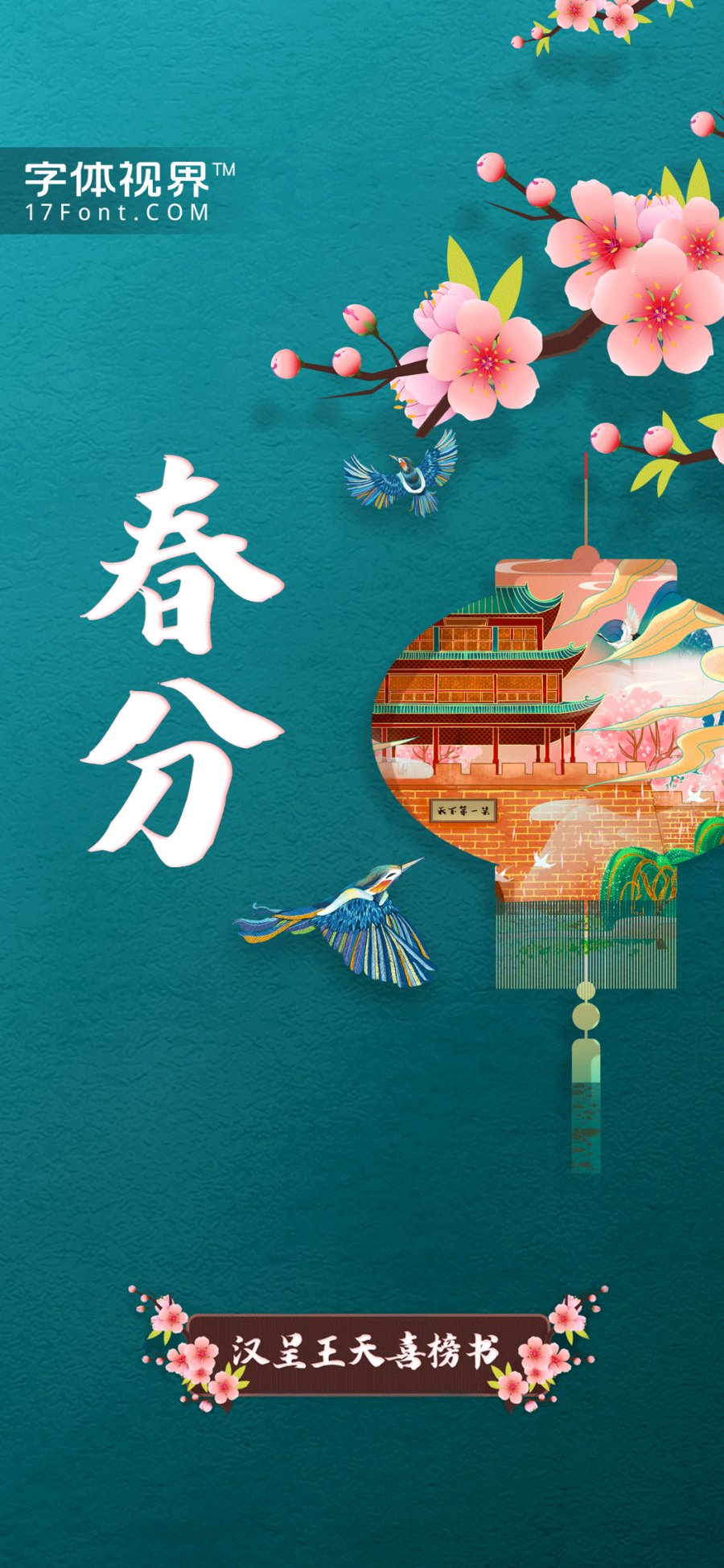
汉呈王天喜榜书字体是典型的行楷字体风格,看上去非常的端正秀美,充满了古典气息。字体可以应用于广告设计。喜欢这款字体欢迎前往字体视界平台官网搜索下载。
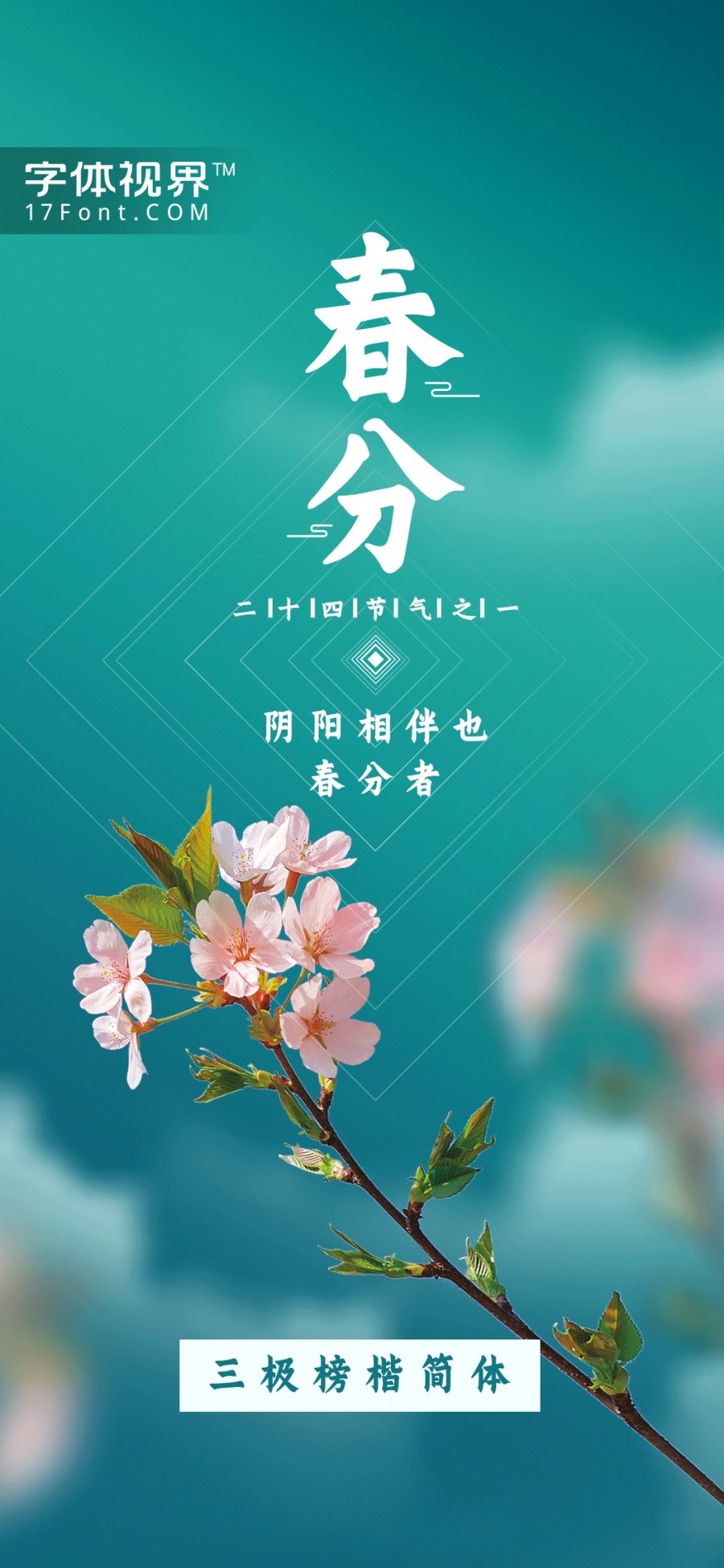
三极榜楷简体字体是由三极字库以传统楷书大字为结构雏形设计的一款简体中文字体,该字体笔画豪迈雄伟,笔墨中正,字形雍容大气,厚重沉稳,极富艺术感染力。适用于各类传统习俗的包装和宣传设计及书法作品排版标题、招牌设计。
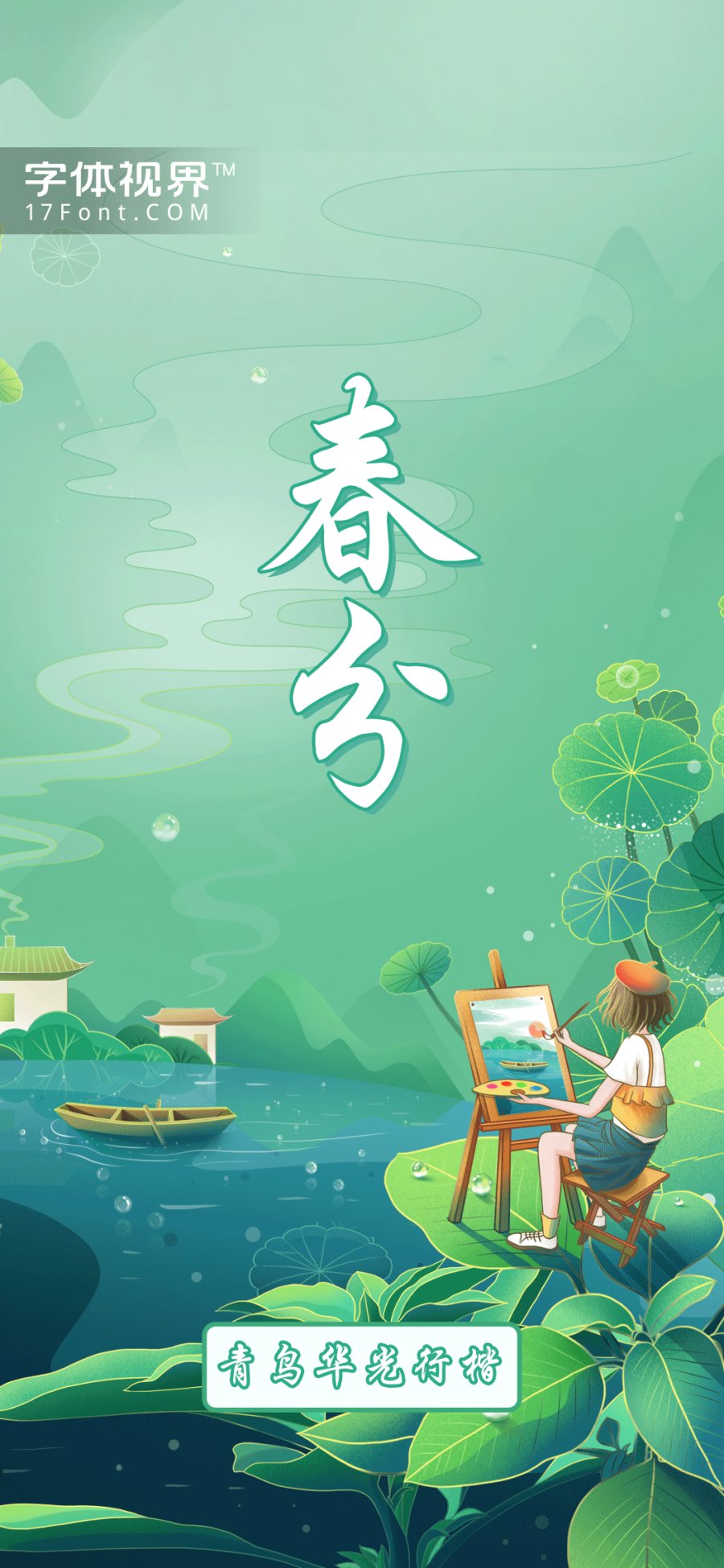
青鸟华光简行楷是一款用于创意设计方面的简体中文字体,该字体以行楷字为原形而设计,线条粗细适中,字形整体效果非常出色,可以广泛应用于广告设计、宣传海报、影视制作等领域。